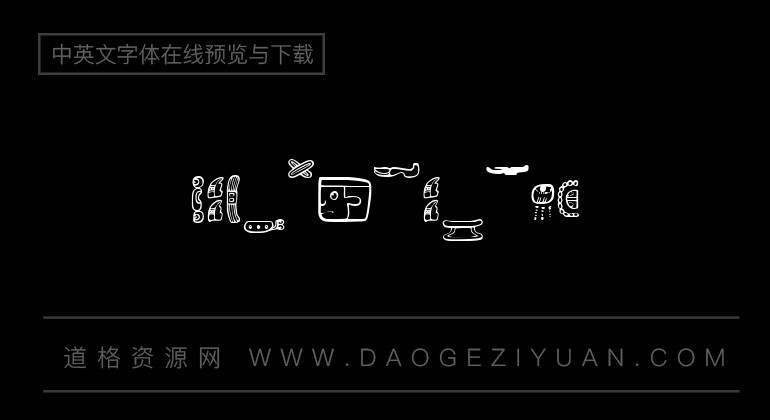
Meso America
Mesoamerica 字体是一种由 Jonathan Perry 设计的字体,灵感来自于玛雅文化和墨西哥文化。它是一种非常具有艺术特色的字体,具有浓郁的手工制作感和自然感。字母形状是基于玛雅文化和墨西哥文化中的图案和纹理设计的,其风格独特,非常适合用于设计徽标,海报,印刷品等。 Mesoamerica 字体包含大写字母,小写字母,数字和标点符号。它有两种版本,一种是常规版本,另一种是轮廓版本。常规版本是填充的字母形状,而轮廓版本只有字母的轮廓。这使得 Mesoamerica 字体非常适合在不同类型的设计项目中使用,可以根据具体需求选择不同的版本。 总的来说,Mesoamerica 字体是一种设计感强烈的艺术字体,非常适合用于文化,传统或手工制作主题的设计项目中。
Meso America是一款非常不错的手写艺术字体,具有很好的视觉感,适合于文化类的宣传设计、商业类品牌的广告和产品包装设计以及个性化文字排版等较多场景。